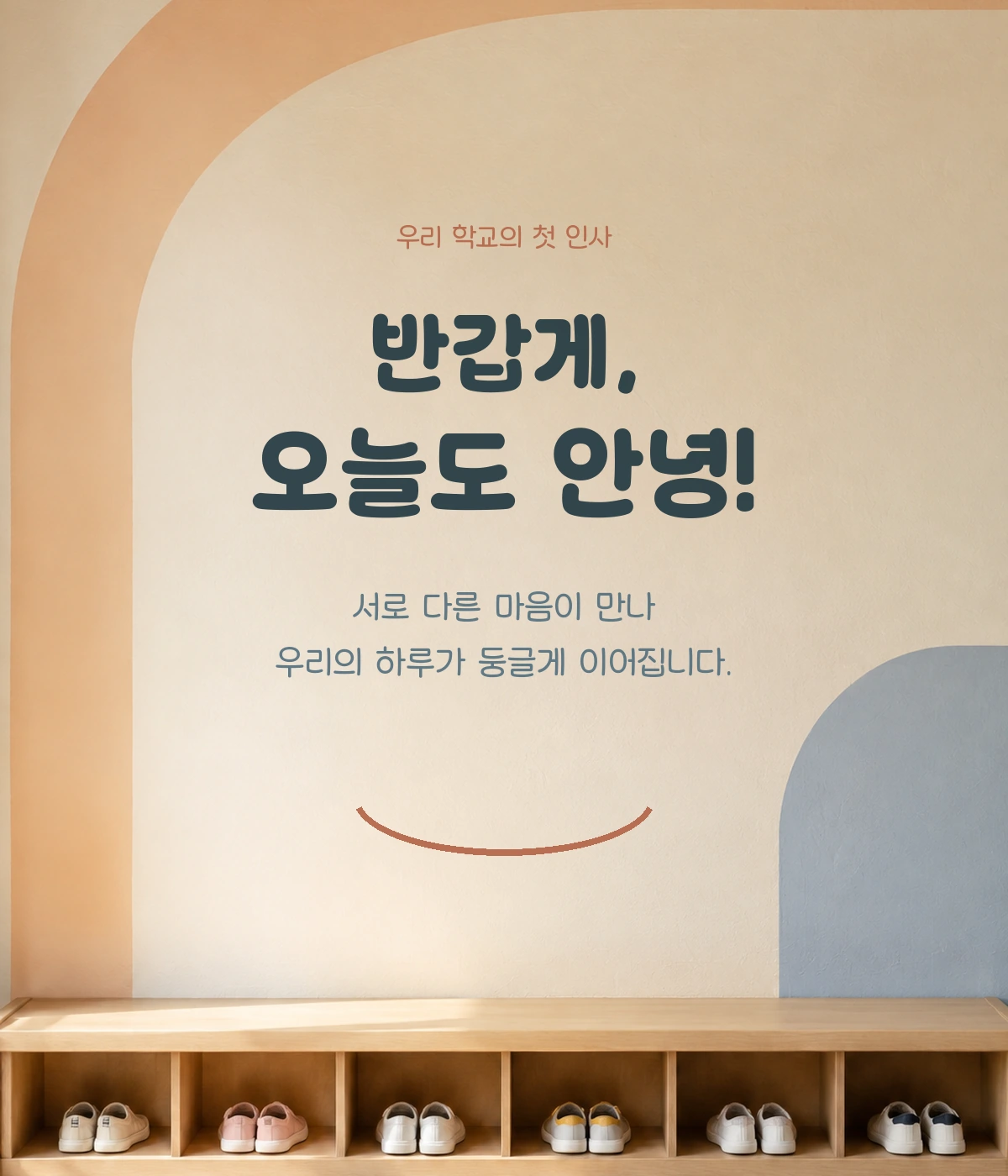
학교안심 둥근미소 무료폰트
학교안심 둥근미소 — Keris에서 배포하는 무료 폰트입니다. 둥글게 굴린 획으로 따뜻한 인상을 내는, 학교에서 저작권 걱정 없이 쓰는 굴림 계열 서체
교육부와 17개 시도교육청, 한국교육학술정보원이 함께 진행하는 학교 안심폰트 사업으로 2024년에 배포된 서체이고 헤움디자인이 제작했습니다. 학교에서 저작권 걱정 없이 수업 자료를 만들 수 있도록 매년 폰트 업체를 공모해 수요가 높은 글꼴을 선정하는 사업입니다.
기관 소개문이 설명하는 조형은 이렇습니다. 둥글게 굴린 자소 형태로 부드럽고 친근한 인상을 주는 타이틀용 서체이고, 여기에 스텐실 스타일을 더해 단순한 귀여움을 넘어선 시각적 포인트를 만들었다는 것입니다. 자소 크기를 크게 설계해 가시성을 높였다는 설명도 붙습니다. 스텐실은 획이 중간에 끊긴 형태를 말합니다.